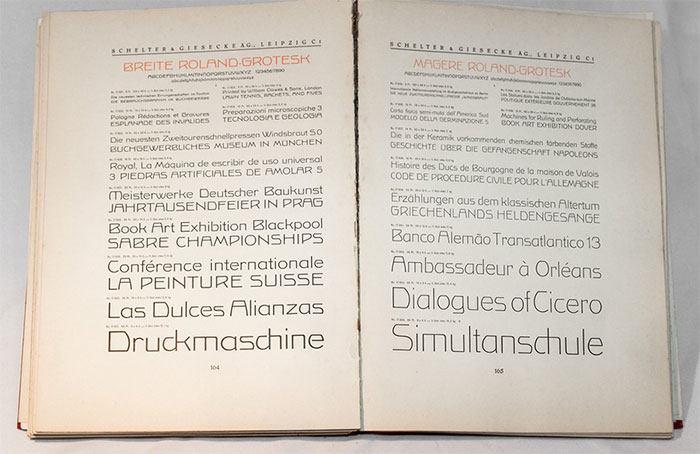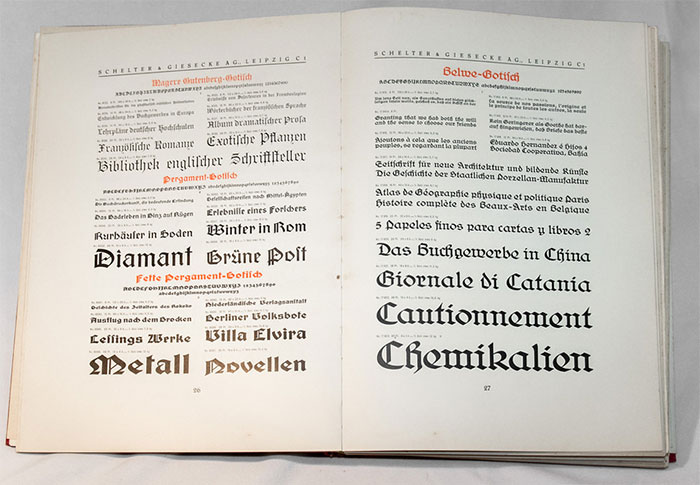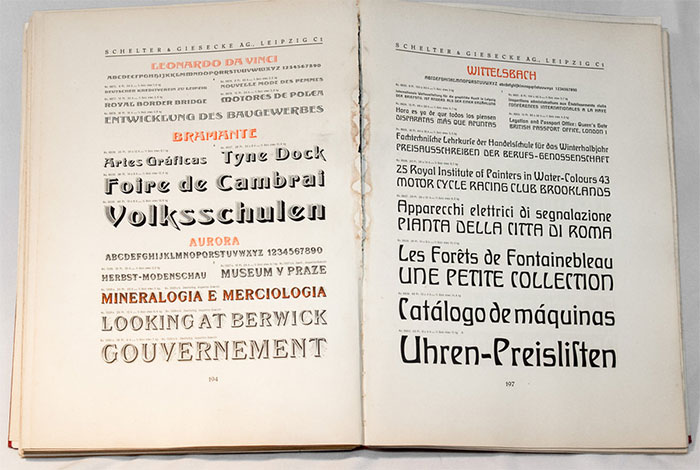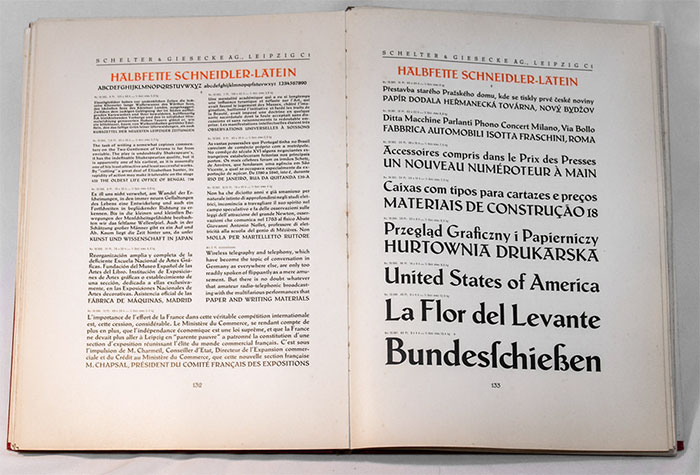
Eine undatierte Schriftprobe der Leipziger Gießerei Schelter & Giesecke, die vermutlich aus den 1930er-Jahren stammt.
Erster Teil: Frakturschriften … Seite 1–40
Zweiter Teil: Antiquaschriften … Seite 41–148
Dritter Teil: Groteskschriften … Seite 149–192
Vierter Teil: Karten- und Reklameschriften … Seite 193–240
- Alt-Latein … 44
- Antiqua 16 … 41
- Antiqua 17 … 42
- Aurora … 194
- Baustein-Grotesk … 185
- Belwe-Antiqua 29 … 115
- Belwe-Gotisch … 27
- Belwe-Kursiv 29 … 118
- Boccaccio … 218
- Borghese … 89
- Bramante … 194
- Breite Antiqua … 49
- Breite Etienne … 57
- Breite fette Antiqua … 54
- Breite fette Egyptienne … 65
Breite fette Grotesk … 160
Breite fette Grotesk-Großbuchstaben … 160 -
Breite fette Koralle … 178
Breite fette Koralle-Schrägschrift … 184 - Breite fette Schelter-Antiqua … 108
- Breite Gnom … 210
Breite halbfette Grotesk … 159
Breite halbfette Grotesk-Großbuchstaben … 158 - Breite halbfette Koralle … 176
- Breite halbfette Schulfraktur … 10
- Breite Koralle … 173
Breite magere Grotesk … 157
Breite magere Grotesk-Großbuchstaben. … 158 - Breite magere Mediäval … 82
- Breite magere Renaissance … 82
- Breite magere Romanisch-Kursiv … 212
- Breite Monos … 201
- Breite Renaissance … 83
- Breite Roland-Grotesk … 164
- Breite Romanisch … 96
- Breite schattierte Italienne … 66
- Breite Schelter-Antiqua 25 … 105
- Breite Schulfraktur 22 … 10
- Breite Shakespeare-Mediäval … 137
- Breite Titan … 203
- Buchdeutsch … 22
- Dolmen … 206
- Eidechse … 211
- Enge Antiqua … 49
- Enge Egyptienne … 60
- Enge fette Steinschrift … 151
- Enge halbfette Schulfraktur … 11
Etienne . … 57
Etienne-Kursiv … 57 - Feenhaar … 213
- Fette Belwe-Antiqua … 123
- Fette Fraktur 6. Garnitur … 5
- Fette Koralle … 177
- Feite Kursiv … 54
- Fette lichte Koralle-Großbuchstaben … 180
- Fette Mediäval … 77
- Fette Parcival-Antiqua … 72
- Fette Pergament-Gotisch … 26
- Fette Rhythmus … 190
- Fette Salzmann-Fraktur … 20
- Fette Schulfraktur … 14
- Fette Shakespeare-Mediäval … 145
- Fette Steinschrift … 156
- Fraktur 17 … 1
Ganz breite Koralle … 174
Ganz breite Koralle-Großbuchstaben … 169 -
Ganz breite zarte Koralle … 171
Ganz br. zarte Koralle-Großbuchstaben … 169 - Große lateinische Schreibschrift … 224
- Großmütterchen … 221
- Habsburg … 196
- Halbfette Aldine … 52
- Halbfette Belwe-Antiqua … 121
- Halbfette Buchdeutsch … 24
- Halbfette Etienne … 58
- Halbfette Gutenberg-Gotisch … 25
Halbfette Koralle … 175
Halbfette Koralle-Schrägschrift … 183 - Halbfette Kursiv-Aldine … 54
- Halbfette Kursiv-Grotesk … 161
- Halbfette lateinische Schreibschrift … 225
- Halbfette Liane … 205
- Halbfette Mediäval-Kursiv … 80
- Halbfette Rhythmus … 188
Halbfette Romanisch … 94
Halbfette Romanisch-Kursiv … 97 - Halbfette Rundgotisch … 36
- Halbfette Salzmann-Antiqua … 114
- Halbfette Salzmannschrift … 29
- Halbfette Schelter-Antiqua … 107
- Halbfelte Schneidler-Latein … 132
- Halbfette Schneidler-Schwabacher … 38
- Halbfette Schulfraktur … 12
- Halbfette Schwabacher … 40
- Halbfette Shakespeare-Mediäval … 143
- Halbfette Shakespeare-Schrägschrift … 147
- Halbfette Sylphide … 214
- Halbfette Tauchnitz-Antiqua … 111
Hochstehende Buchstaben (Superieurs),
Römische Ziffern und Bruchziffern zu Schreibschriften … 227 - Isabel … 215
- Italienne … 55
- Kartenschrift Breite Gnom … 210
- Kartenschrift Gnom … 208
- Kartenschrift Kolibri … 210
- Kartenschrift Perkeo … 209
- Kleine lateinische Schreibschrift … 224
- Kolibri … 210
- Koralle … 172
- Kräftige Salzmann-Fraktur 24 … 17
- Künstler-Grotesk … 212
- Kurante halbfette Fraktur … 3
- Kursiv 18 … 46
- Leonardo da Vinci … 194
- Liane … 204
- Lichte Belwe-Antiqua … 124
- Lichte Wallenstein … 195
- Lichte-Wieland … 223
- Lincoln … 193
- Magere Egyptienne … 62
- Magere Gutenberg-Gotisch … 26
- Magere Roland-Grotesk … 165
- Magere Romanisch … 89
- Mediäval-Antiqua 15 … 73
- Mediäval-Antiqua 19 … 76
- Mediäval-Athenienne … 56
- Mediäval-Egyptienne … 78
- Mediäval-Kursiv 15 … 75
- Mediäval-Schreibschrift … 215
- Mediäval-Steinschrift … 161
Mischprobe der Breiten mageren Grotesk
mit Breiter halbfetter Grotesk … 157 - Moderne enge halbfette Fraktur … 2
- Moderne fette Antiqua … 53
- Moderne fette Fraktur 5. Garnitur … 5
- Moderne schmale halbfette Antiqua … 50
- Monogramme … 230
- Monos … 200
- Murillo … 199
- Parcival-Antiqua … 67
- Parcival-Kursiv … 70
- Pennsylvania … 77
- Pergament-Gotisch … 26
- Perkeo … 209
- Petrarka … 198
- Propaganda … 218
- Radium … 198
- Rautendelein … 226
- Reklameschrift Thor … 125
- Rhythmus … 186
- Rienzi (Großbuchstaben) … 158
Roland-Grotesk … 162
Roland-Grotesk-Kursiv … 166 -
Romanisch-Antiqua 20 … 84
Romanisch-Antiqua 20, Großbuchstaben … 87 -
Romanisch-Antiqua 22 … 88
Romanisch-Kursiv 20 … 90 - Rousseau … 217
Rundgotisch … 31
Rundgotisch-Kursiv … 34 - Rundschrift … 214
- Salamander … 211
- Salzmann-Antiqua 28 … 112
- Salzmann-Fraktur 23 … 15
- Salzmann-Kursiv 28 … 114
- Salzmannschrift … 28
- Saskia . … 191
- Schattierte Egyptienne … 66
Schelter-Antiqua 24 … 99
Schelter-Antiqua 24, Großbuchstaben … 102 - Schelter-Kursiv 24 … 103
- Schlanke Grotesk … 149
- Schlanke halbfette Egyptienne … 63
- Schmale englische Antiqua-Aldine … 48
- Schmale fette Aldine … 51
- Schmale fette Egyptienne … 64
- Schmale fette Koralle … 179
- Schmale fette Schelter-Antiqua … 106
- Schmale fette Schreibschrift … 225
- Schmale fette Schulfraktur … 13
- Schmale fette Steinschrift … 153
Schmale Grotesk … 150
Schmale Grotesk-Großbuchstaben … 150 - Schmale halbfette Fraktur 3. Garnitur … 4
- Schmale halbfette Mediäval … 81
- Schmale halbfette Romanisch … 93
- Schmale halbfette Rundgotisch … 35
- Schmale halbfette Salzmann-Fraktur. … 19
- Schmale halbfette Shakespeare-Mediäval … 141
- Schmale halbfette Steinschrift … 152
- Schmale magere Egyptienne … 61
- Schmale Mediäval … 81
- Schmale Roland-Grotesk … 163
- Schmale Romanisch … 92
- Schmale Rundgotisch … 33
- Schmale Salzmann-Fraktur … 16
- Schmale Salzmannschrift … 30
- Schmale Steinschrift … 149
- Schneeflocke … 193
- Schneidler-Fraktur … 21
- Schneidler-Latein … 126
- Schneidler-Schrägschrift … 129
- Schneidler-Schwabacher … 37
- Schraffierte Fafner … 167
- Schraffierte Koralle … 181
- Schreibmaschinenschriften … 228
- Schulfraktur 18 … 6
- Schulfraktur 19 … 8
- Schulfraktur 20 … 9
- Schwabacher … 39
- Shakespeare-Mediäval … 134
- Shakespeare-Schrägschrift … 138
- Steinschrift 1. Garnitur … 154
- Steinschrift 2. Garnitur … 155
- Sylphide … 214
- Tauchnitz-Antiqua 27 … 109
- Tauperle … 207
- Tausendschön … 226
- Umstochene Etienne … 59
- Umstochene Mediäval-Schreibschrift … 216
- Voltaire … 216
- Vulkan … 219
- Walgunde … 219
- Wallenstein … 195
- Watteau … 220
- Wettin … 196
- Wieland … 222
- Wittelsbach … 197
Zarte Koralle … 170
Zarte Koralle-Großbuchstaben … 169 -
Zarte Koralle-Schrägschrift … 182
Zarte Koralle-Schrägschrift-Großbuchst. … 169 - Zierbuchstaben … 232
- Zierbuchstaben zur Großmütterchen … 221
- Zierbuchstaben zur Watteau … 220
- Zierdolmen … 207
- Zierschrift … 56